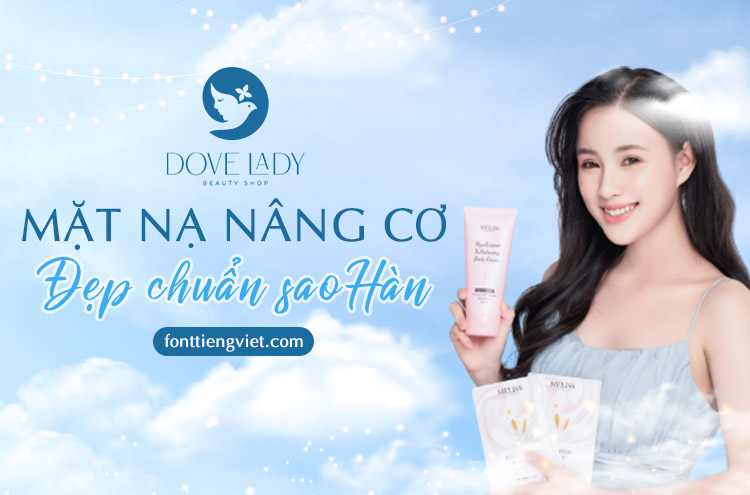
Font combo thiết kế mỹ phẩm 3 – Sẳn hiệu ứng trong file Ps
Font combo thiết kế mỹ phẩm 3 – Sẳn hiệu ứng trong file Ps và giải pháp đồ họa chuyên nghiệp
Giới thiệu về Font combo thiết kế mỹ phẩm 3 – Sẳn hiệu ứng trong file Ps
Trong ngành công nghiệp làm đẹp đầy tính cạnh tranh hiện nay, việc sở hữu một bộ nhận diện thương hiệu ấn tượng là yếu tố then chốt để thu hút khách hàng. Bộ Font combo thiết kế mỹ phẩm 3 – Sẳn hiệu ứng trong file Ps ra đời như một giải pháp hoàn hảo cho các nhà thiết kế và chủ doanh nghiệp muốn tối ưu hóa quy trình sáng tạo. Đây không chỉ đơn thuần là các kiểu chữ thông thường mà là một hệ thống thiết kế đồng bộ, giúp bạn tạo ra những bao bì sản phẩm, poster quảng cáo hay hình ảnh truyền thông trên mạng xã hội một cách nhanh chóng và đẳng cấp nhất. Việc tìm kiếm một Font Miễn Phí phù hợp để làm nổi bật sự sang trọng của mỹ phẩm chưa bao giờ dễ dàng đến thế khi bạn sở hữu bộ sưu tập đặc biệt này trong tay.
Tại sao nên chọn Font combo thiết kế mỹ phẩm 3 cho dự án của bạn
Bộ font này được tuyển chọn kỹ lưỡng để phản ánh sự tinh tế, thanh lịch và hiện đại – những đặc tính cốt lõi của các dòng mỹ phẩm cao cấp. Thay vì phải mất hàng giờ để căn chỉnh từng đường nét hay đổ bóng cho chữ, Font combo thiết kế mỹ phẩm 3 – Sẳn hiệu ứng trong file Ps đã tích hợp sẵn các Layer Style trong Photoshop. Điều này có nghĩa là người dùng chỉ cần thay đổi nội dung văn bản, các hiệu ứng như ánh kim, đổ bóng đổ nổi hay chất liệu satin sẽ tự động áp dụng, giữ nguyên vẻ chuyên nghiệp mà không đòi hỏi kỹ năng đồ họa quá chuyên sâu. Sự kết hợp giữa các font chữ không chân (Sans-serif) hiện đại và các font chữ viết tay (Script) mềm mại tạo nên một sự tương phản đầy tính nghệ thuật, giúp thông điệp của thương hiệu trở nên dễ nhớ và cuốn hút hơn bao giờ hết đối với người tiêu dùng.
Cách sử dụng Font combo thiết kế mỹ phẩm 3 – Sẳn hiệu ứng trong file Ps hiệu quả
Để tận dụng tối đa sức mạnh của bộ công cụ này, bạn cần hiểu rõ cách vận hành của các tệp tin PSD đi kèm. Mỗi tệp tin được cấu trúc rõ ràng với các lớp (layer) được đặt tên cụ thể, giúp việc tùy chỉnh trở nên trực quan. Bạn có thể thay đổi màu sắc để phù hợp với tông màu chủ đạo của nhãn hàng hoặc điều chỉnh độ sáng tối của hiệu ứng chỉ với vài cú nhấp chuột. Font combo thiết kế mỹ phẩm 3 – Sẳn hiệu ứng trong file Ps cực kỳ linh hoạt, cho phép bạn ứng dụng từ thiết kế vỏ hộp, nhãn chai lọ cho đến các banner khuyến mãi trên website. Đặc biệt, đối với các bạn học sinh, sinh viên đang theo học ngành thiết kế, đây là tài liệu tham khảo quý giá để hiểu về cách phối hợp typography và hiệu ứng hình ảnh trong thực tế sản xuất thương mại.
Lưu ý khi thiết kế đồ họa ngành mỹ phẩm
Khi sử dụng bộ font này, hãy chú ý đến khoảng cách giữa các chữ cái (kerning) và dòng (leading) để đảm bảo tính dễ đọc trên các bề mặt nhỏ như thỏi son hay hộp kem dưỡng da. Việc lạm dụng quá nhiều hiệu ứng có thể làm mất đi sự tinh tế, vì vậy hãy biết cách tiết chế và chọn lọc những điểm nhấn quan trọng nhất. Sự đồng nhất về font chữ trên mọi nền tảng sẽ giúp khách hàng nhận diện thương hiệu của bạn một cách tốt hơn giữa hàng nghìn sản phẩm khác trên kệ hàng.
Kết luận về bộ Font combo thiết kế mỹ phẩm 3